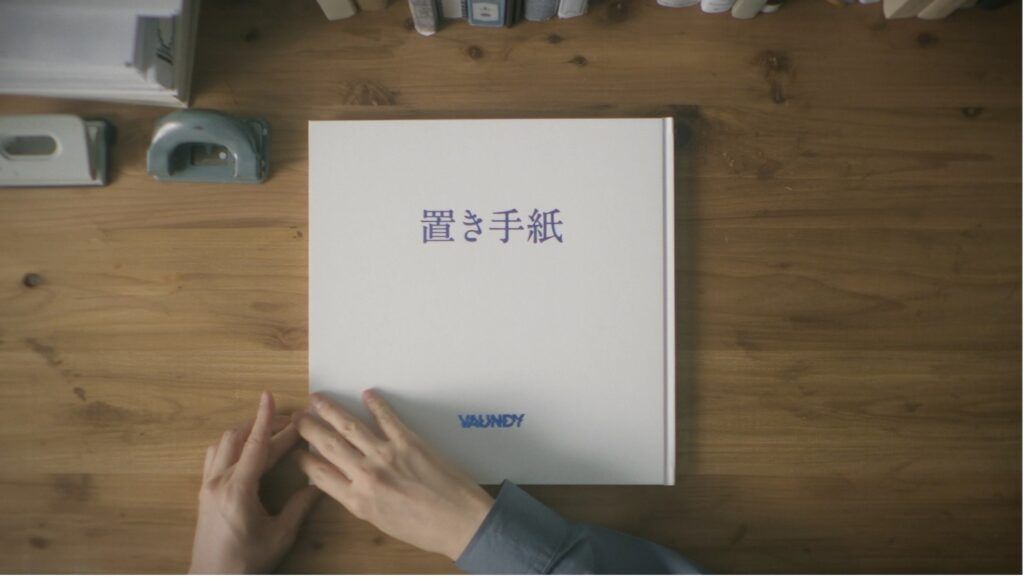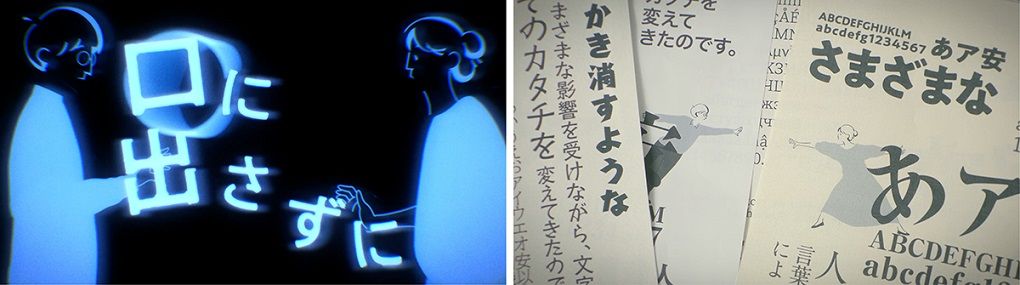
モリサワ Morisawa FontsとコラボしたVaundyの楽曲「置き手紙」MVが「Spikes Asia 2023」のフィルムクラフト部門ブロンズ受賞
株式会社モリサワが提供している『Morisawa Fonts』とコラボしたVaundy氏の楽曲「置き手紙」のミュージックビデオ(MV)が、アジア最大級の広告コミュニケーションフェスティバルでもあるカンヌライオンズのアジア地域版フェスティバル「Spikes Asia 2023」において、フィルムクラフト部門でブロンズ受賞を受賞した。
加えて、音楽部門の最終候補作品にも選出された。
受賞した楽曲「置き手紙」MVは、言葉に込められた想いを幅広く表現できるフォントの可能性をテーマに据え、Morisawa Fontsから選ばれた77書体が歌詞を彩る映像作品。クリエイティブディレクター川村真司氏がCCOを務める株式会社ワットエバー(以下Whatever)と、実写・アートワーク・アニメーションなどを総合的に手がける牧野惇氏を監督に迎え制作された。
クラフト的な独特の手法を駆使した約4分30秒の映像世界に、書体見本帳を軸とした物語が展開され、リリックビデオを超えた新しい文字表現が誕生した。
特設サイトでは、MVのフルバージョンのほか、登場するすべての歌詞と使用フォントを詳しく紹介している。また、Vaundy氏、クリエイティブを担当したWhatever 川村真司氏、監督の牧野惇氏に、制作の背景や見どころについてのスペシャル対談も掲載している。